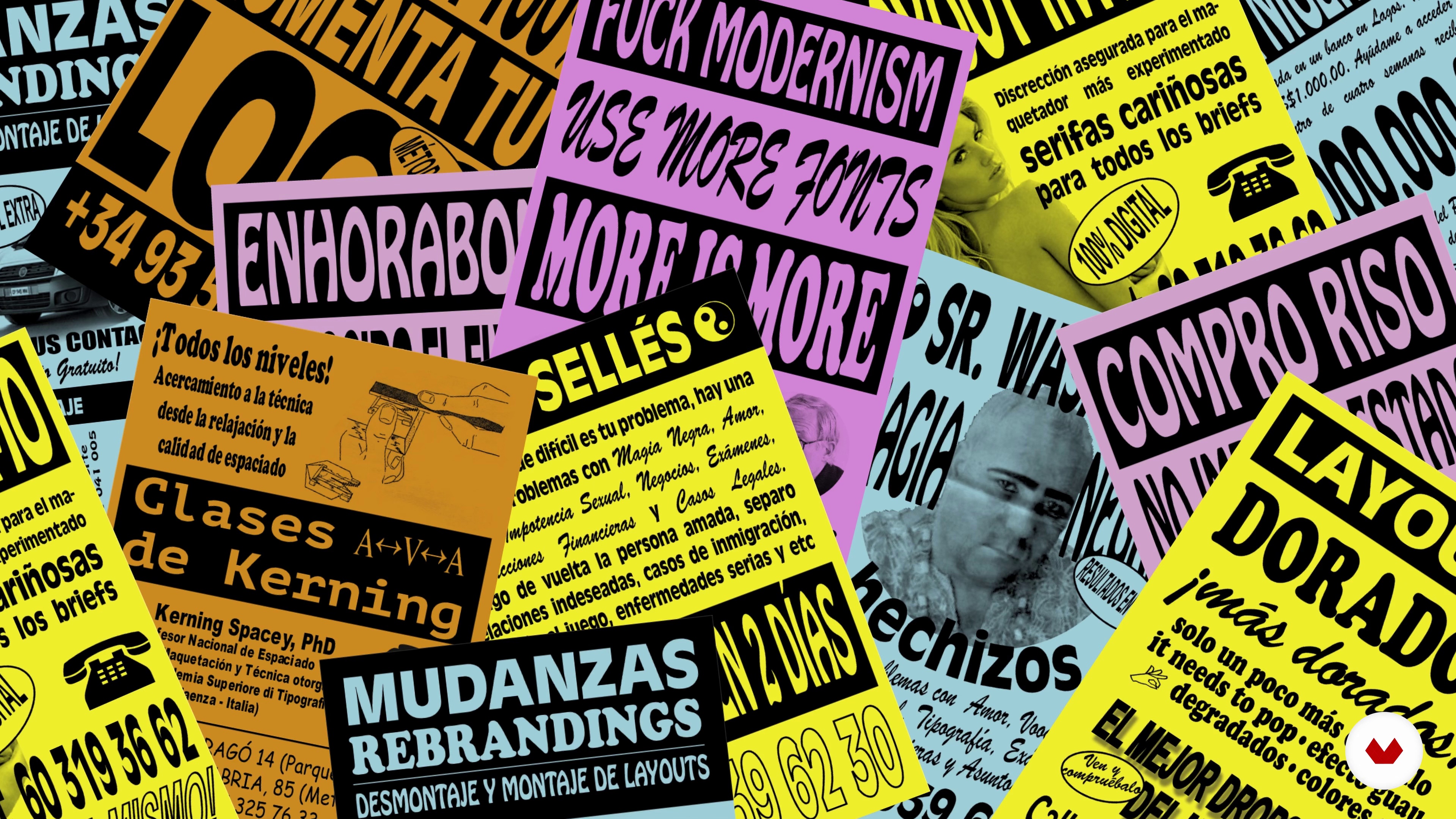
“Aqui, darei mais exemplos e continuarei explicando os fatores que temos que levar em conta na hora de combinar fontes. Além disso, você verá que duas famílias podem interagir de muitas maneiras para aprimorar um projeto. ”
Nesta videoaula, Álvaro Franca aborda o tópico: Combinando fontes 2,que faz parte do curso online da Domestika: Fundamentos da tipografia de A a Z. Descubra as possibilidades da seleção tipográfica para transmitir e potencializar sua mensagem .
“Combinando fontes Esse outro exemplo que eu gosto joga muito com o contraste no título, então você tem uma fonte atrás que é supergrossa, superextensa, sem nenhum detalhe, combinada com uma fonte que é 100% detalhe. E que ela é bem fina e ela é bem compacta, então no mesmo espaço onde cabiam uma palavra de quatro letras, nessa outra fonte, cabe uma palavra muito maior. Isso está avançando um pouco a história do filme que usa a estética das luzes que tem a ver com personagens "food truckers". Estou usando um contraste superextremo, mas apoiado num ponto de estabilidade, que é o texto corrido...”